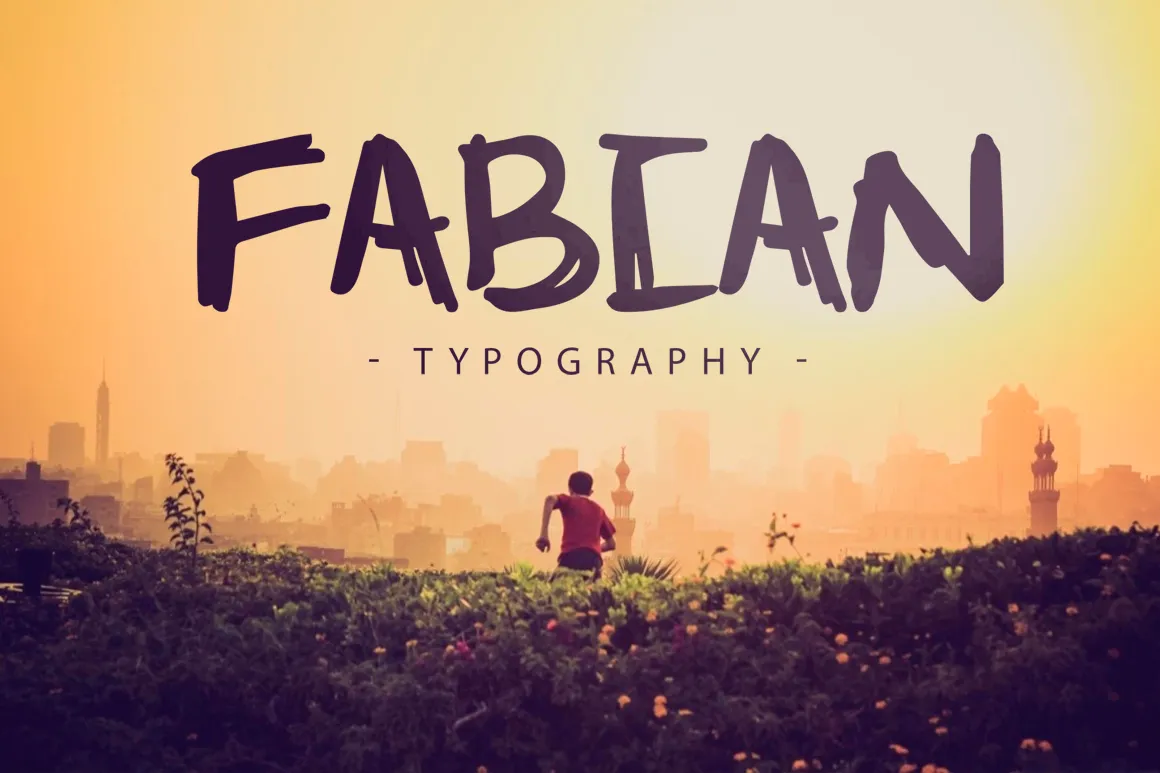
A fonte ‘Fabian’s Name’ é uma tipografia escrita a mão criada por Hamilton que reflete a serenidade do seu título. Conforme projetada para adicionar um toque de personalização aos seus materiais digitais, essa fonte se destacará com suas linhas curvas sutis e formas suaves que lembram escrevermos à mão. Ela é perfeita tanto para criações de emails quanto para design gráfico que buscam uma atmosfera natural e envolvente. A ‘Fabian’s Name’ é uma escolha ideal para quem busca um touch criativo sem sacrificar a funcionalidade, oferecendo uma maneira elegante de incluir seu sotaque ou apelido nas suas criações digitais. Esta fonte manuscrita não apenas reforça sua individualidade mas também se torna uma parte intrínseca da identidade visual das suas produções.